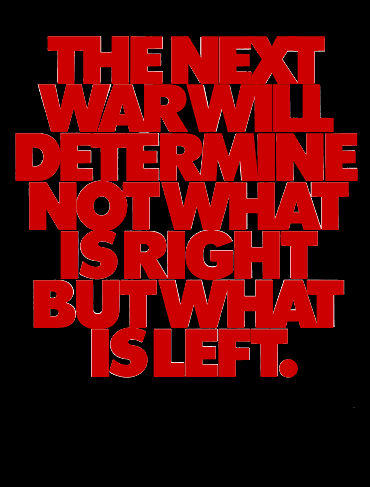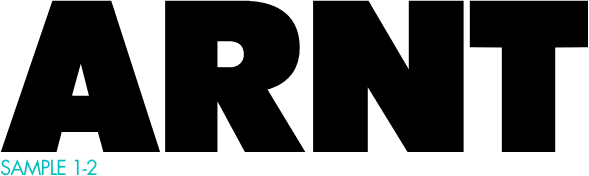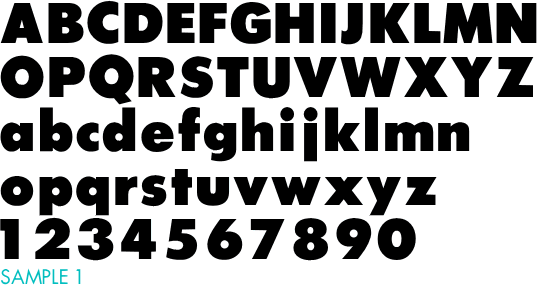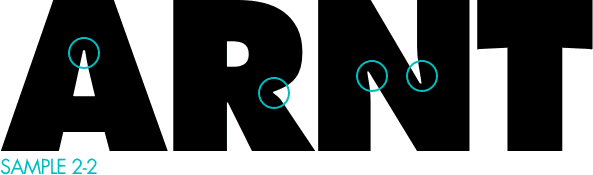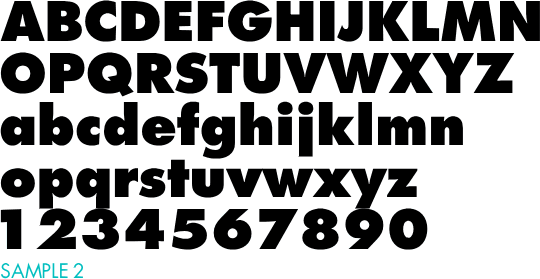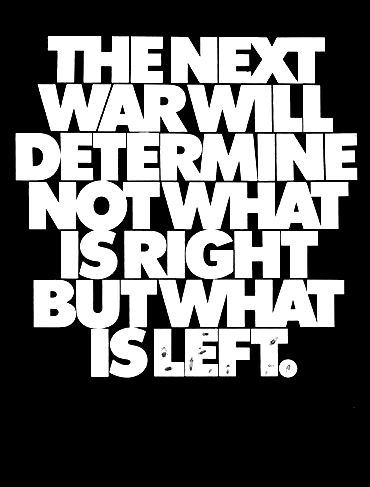
フーツラを使っていて気づいたこと。
エクストラボールドには大きく分けて、2種類が存在するようです。
サンプルを見比べてください。
各画像の右側は、そのスタイルを採用したフォントメーカーです。
全体的に微妙に違いますね...。
「G」「Q」「g」「5」は決定的に違います。
拡大すると...。
サンプルAは、接続点にくぼみがあり、「T」のバーが垂れ気味です。
ずっとこれに違和感があったんです。
※
Scangraphic 社のものはAのスタイルでありながら、くぼみや垂れはなく、
Berthold 社製に限っては、ふたつをミックスしたようなデザインです。
フーツラはパウル・レナーによってデザインされ、1928年に Bauer 社よりリリース。
1999年、フーツラの版権を持つ同社は、Neufville 社にデジタル化を依頼しました。
実は「Futura Extra Bold」とイタリックに関しては、パウル・レナーによるデザインではなく、
Intertype 社の Edwin W. Shaar によるデザインで、1952年にリリースされたようです(通称「Intertype Futura」
)。
ちなみに、Linotype 社は「Spartan」、Intertype
社は「Vogue」というフーツラそっくりの書体をリリースしています。
| Date |
Typefaces and Weights |
Designers |
Foundry |
| 1928 |
Futura Light, Medium, Bold, Bold Oblique |
Paul Renner |
Bauer |
| 1929 |
Futura Black |
Paul Renner |
|
| 1930 |
Futura Light Oblique, Medium Oblique, Demibold,
Demibold Oblique |
Paul Renner |
Bauer |
| 1932 |
Futura Book |
Paul Renner |
Bauer |
| 1932 |
Futura Display (Futura Schlagzeile) |
Paul Renner |
Bauer |
| 1936-1952 |
Steile Futura |
Paul Renner |
|
| 1939 |
Futura Book Oblique |
Paul Renner |
Bauer |
| 1952 |
Futura Extra Bold |
Edwin W. Shaar |
Intertype |
| 1955 |
Futura Extra Bold Italic |
Edwin W. Shaar
Tommy Thompson |
Intertype |
| 1936-1947 |
Twentieth
Century |
Sol Hess |
Monotype |
| 1960 |
Futura Maxi |
Victor Caruso |
Photo-Lettering Inc. |
| 1991 |
Century Gothic |
|
Monotype |
ふたつのサンプル、一体、どちらが本来の「Futura Extra Bold」なのでしょうか?
1972年にデザインされたハーブ・ルバーリンのポスターを見てください。
|
Herb Lubalin, 1972 |
@のフーツラですね。
右は@を重ねたものですが、ほぼ一致します。
ここで忘れてならないのが、「Twentieth Century」の存在です。
フーツラをベースにし、1936-1947年に掛けて Sol Hess によってデザインされた書体です。
もしかして、このポスターの書体は「Twentieth Century」なのか?
「Twentieth
Century Ultra Bold」と@を重ねてみると...。
違うんですよね...。
また、「Flyer」という@にそっくりなレア書体がありますが、それでもありません。
書体見本帳を調べてみると...
| 書籍名 |
発売年 |
スタイル |
| Homage to the Alphabet 欧文書体集 1488 |
1991年 |
@ |
| VGC Alphabet Library |
1990年 |
@ |
| Mecanorma Graphic Book 14 |
1988年 |
A(Neufville) |
おそらく、Image Club Graphics 社製の@は Intertype 社の「Futura Extra
Bold」をフォント化したもので、
こちらがオリジナルなのような気がします。